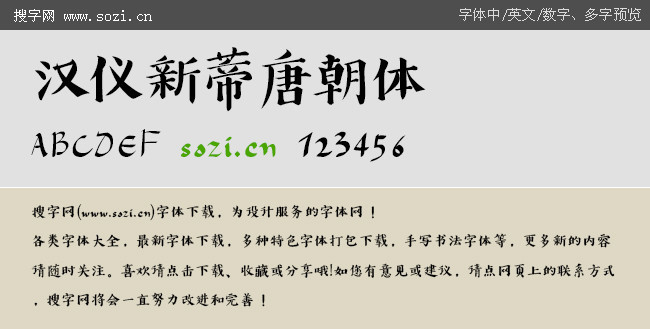
漢儀新蒂唐朝體
搜字網(wǎng)給大家提供一款漢儀新蒂唐朝體中文字體下載,漢儀新蒂唐朝體字體是一款具有唐朝風(fēng)格的漢儀字體,這款字體帶有古典、浪漫的氣息,一筆一畫一絲不茍,粗細(xì)相間,優(yōu)雅氣息十足,適合應(yīng)用于書籍設(shè)計(jì)、平面海報(bào)設(shè)計(jì)、包裝設(shè)計(jì)等廣告應(yīng)用。(本字體為個(gè)人非商用版,如需要商用請(qǐng)聯(lián)系漢儀公司購(gòu)買版權(quán))